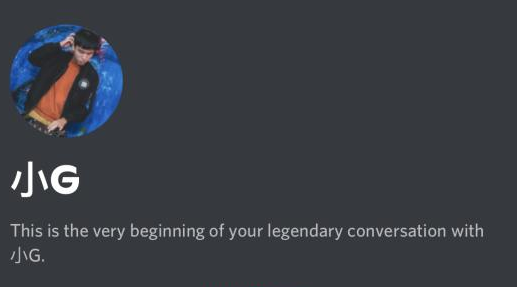
Wer kennt diese spezielle Form von Buchstaben?
Diesmal mit einem ganz speziellem Anliegen:
In dem Discord-Server dem ich angehöre, war kürzlich ein Besucher drin, der besagte Besucher, hatte einen seltsamen Nickname.
Nicht nur das war seltsam sondern, dieser hatte nämlich in seinen Nickname 2 seltsamen Buchstaben auch noch drin, siehe unten.
Daher meine Frage, weiß jemand:
1. Was das G für eine Schriftart ist?
2. Was für ein Land oder welcher Nationalität gehört dieser wohl an, weil der Besucher schreibt ein J mit so ner Art Apostroph / Umlaut oder wie man das auch nennen soll?
Für die Zukunft, einfach das Zeichen digital kopieren. Dann kannst du im Internet danach suchen. Am besten auf Seiten wie https://graphemica.com
Die können Zeichenketten in alle Bestandteile zerlegen und die beteiligten Zeichen erklären. Wenn nur die Form bekannt ist, dann eine Seite Shapecatcher helfen.
Muss jetzt nochmal nachfragen, wie meinst du genau digital kopieren?
Das Bild habe ich leider nicht gemacht, sondern ein Kollege von mir und es mir dann geschickt.
Muss jetzt nochmal nachfragen, wie meinst du genau digital kopieren?
In Catfonts Beitra kann man das 小 markieren und kopieren und irgendwo anders einfügen, bspw. in der Wikipedia, wo man dann zu einem Atikel über diesen Buchstaben kommt.
Oder beim schnellen Blick in meine Bookmarks könnte man es bspw. auch dort reinkopieren: https://graphemica.com/
Muss dann halt der Kollege machen ...
Und ich kannte das Zeichen 小  eben vom Hersteller meines Smartphones, der 小米  heist, (Xiǎomĭ).
Chinesische Markennamen sind oft recht ulkig. Google übersetzt  小米  mit Hirse, wörtlich von den Schriftzeichen her eher ist es "kleiner Reis" - Anscheinend ist auch deren Reis erheblich größer geworden, denn ihre Marke haben sie jetzt auf MI verkürzt, also 米 = Reis, in einer Schriftart ähnlich Stop, jedoch das I ohne i-Punkt, wobei dieses  Logo in lateinischer Schrift auf den Kopf gestellt dann eine vereinfachtes Zeichen für Herz. Wie Lei Jun  (der CEO)  betont.
So, mehr zum  小  fällt mir jetzt nicht ein.
xiao vor dem Familiennamen als Anrede für den/die jüngere(n) Bekannte(n), lao vor dem Namen für den/die ältere(n). »Xiao G« wäre als »der/die jüngere G« …